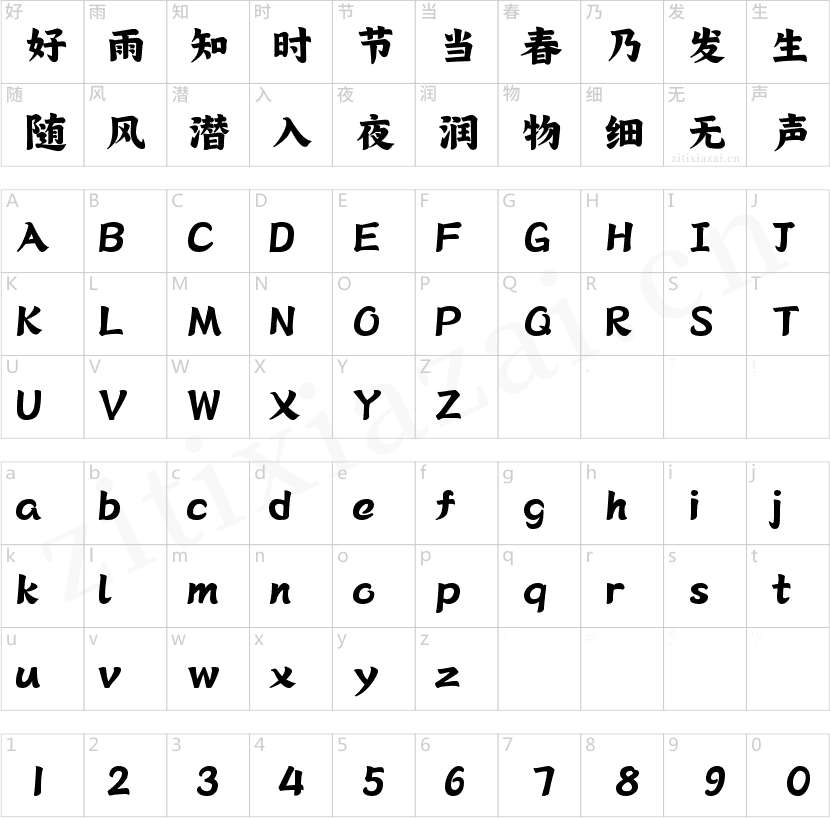
字魂唐宫夜宴体
字体说明:为呼应IP所展现的盛唐时代,字体以唐时书法代表的楷书作为基调。 为了体现传统文化复兴的主题,整套字体字形设计得较为端正、具有古朴韵味。 字体笔画少有粘连,会根据需要来断笔避让, 也让这款字保有着书写阅读的节奏感,像舞蹈表演一般精彩而有序。《唐宫夜宴》是郑州歌舞剧院舞蹈作品,曾入围第十二届中国舞蹈“荷花奖”古典舞评奖终评。创作灵感来自珍藏于河南博物院中的河南巩义北窑湾唐墓出土的三彩女俑。舞蹈高度还原唐代审美,将观众带回一千三百年前盛唐时期的宫廷夜宴。